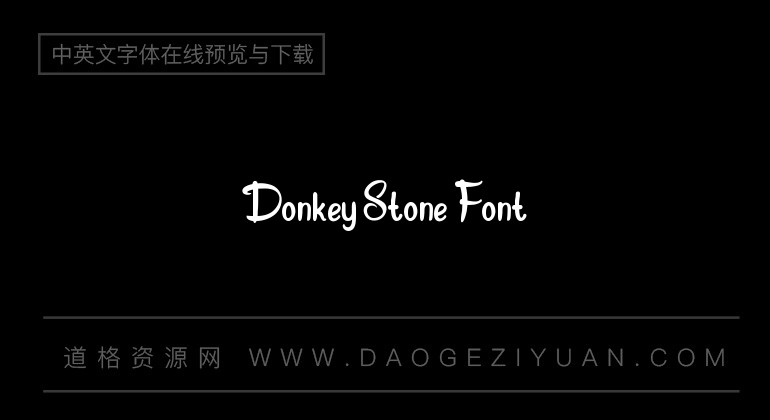
Donkey Stone Font 是一种具有手写风格的字体,它的设计灵感来自于19世纪英国工人使用的打磨石头。因为那时的打磨石头会被称为“驴石”(Donkey Stone),所以这种字体也以此命名。 Donkey Stone Font 的字母形状和笔画都非常有特色,呈现出一种手工制作的感觉。它的外观非常适合用于书籍封面、海报、招贴等设计作品中,或者用于印刷品的配文和标题。 此外,Donkey Stone Font 支持多种语言,包括英语、西班牙语、德语、法语和意大利语等,因此在跨国设计领域中也具有一定的优势。内容介绍
Donkey Stone Font是一款非常不错的手写艺术字体,具有很好的视觉感,适合于文化类的宣传设计、商业类品牌的广告和产品包装设计以及个性化文字排版等较多场景。